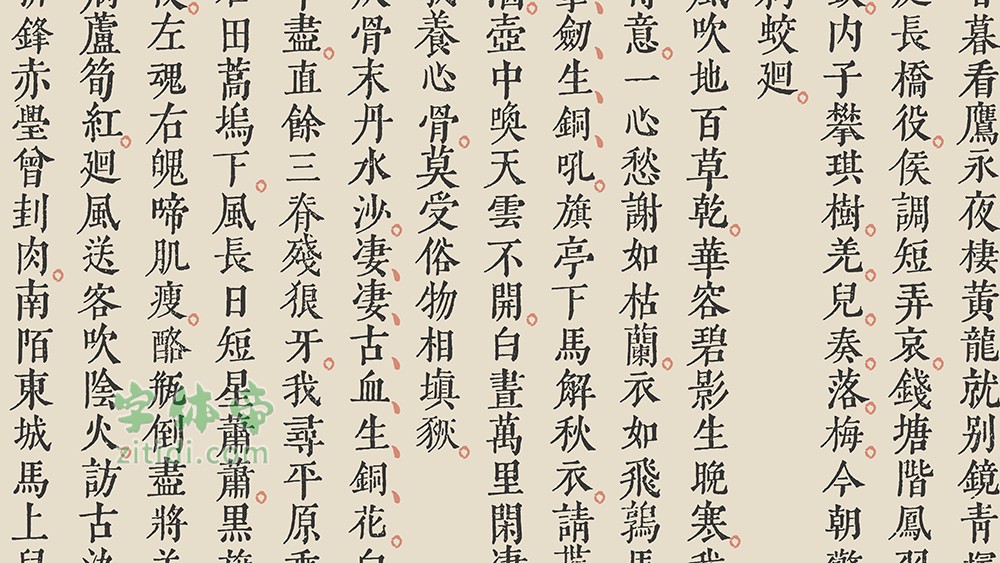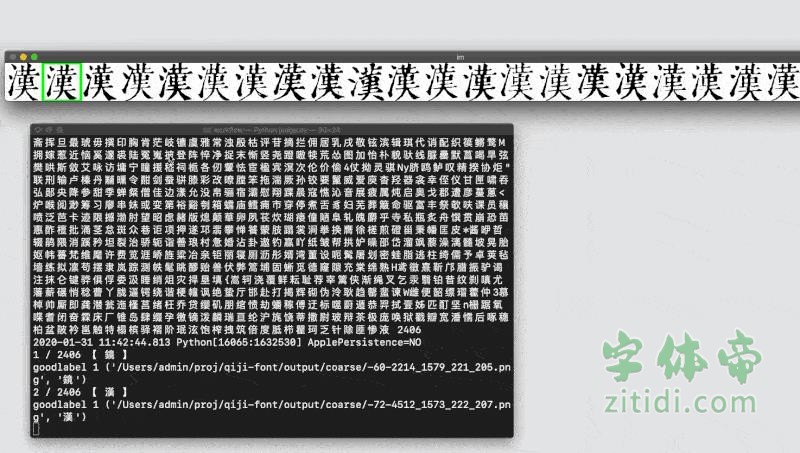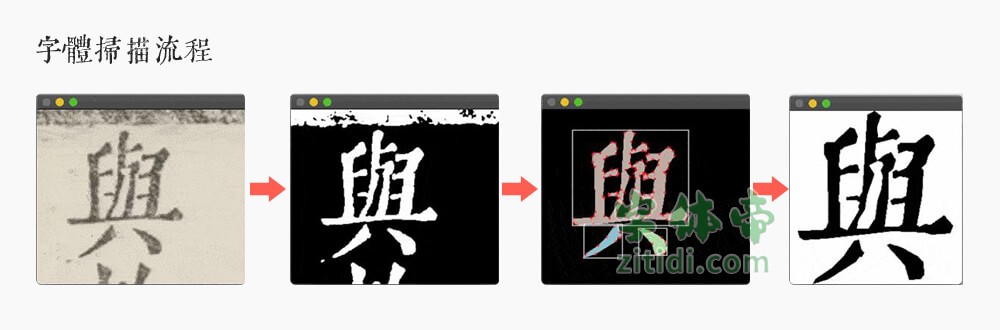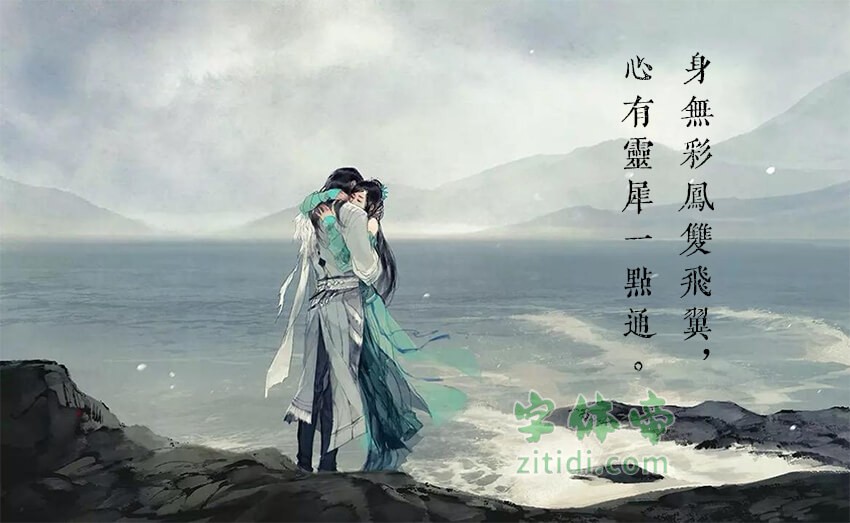
黄令东齐伋复刻采用半自动计算机视觉和OCR对《李長吉歌詩》和《淮南鴻烈解》进行扫描,通过程序处理后再手动选择适合的字型,最后导出成字体文件。
在扫描完字体之后,再从中挑选合适合的字形进行微调处理,最后再把结果输出为字体文件。
黄令东齐伋复刻是对古籍进行处理而得到的字体,所以只有繁体字形。在使用字体的过程中,如果输入简体字会直接映射成繁体字形。比如说你输入“汉”字,出来的结果会是“漢”字。这个结果不难理解,古人不会写简体字。